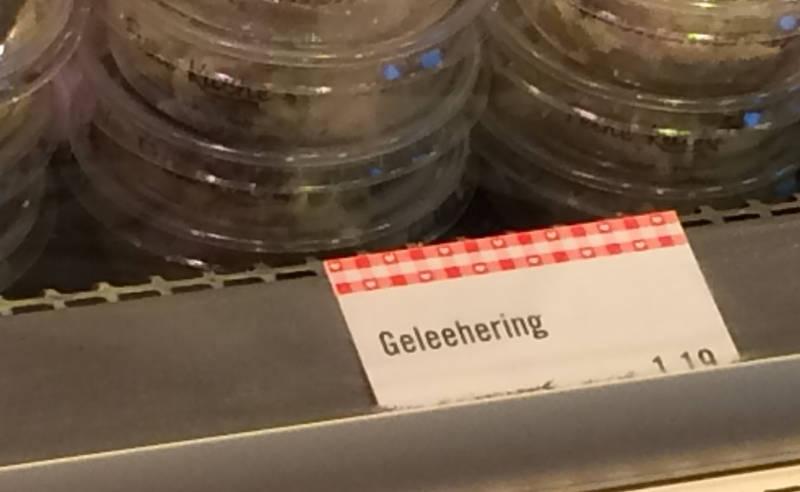
Linzer gibt’s, warum nicht auch Konzer? :-P
Eben: Konz (von lateinisch Contionacum) ist eine Stadt im Landkreis Trier-Saarburg in Rheinland-Pfalz. Sie ist Verwaltungssitz der Verbandsgemeinde Konz, der sie auch angehört. Konz ist ein staatlich anerkannter Fremdenverkehrsort. Warum soll es da nicht eine ortstypische Torte geben?
Neuer Trend für Frisch-Vermählte mit Metallallergien: der Gelee-Ehering, hier im Foto allerdings noch nach vorreformierter Rechtschreibung ohne dreifach-e.
Knifflig auszusprechen: Geschäftschance
Ich verstehe das so: :-P
• Ursprünglich schrieb man Geschäftchance oder Geschäft-Chance
• Der Rat für deutsche Rechtschreibung deutete es volksetymologisch so, daß eine Chance wie ein Sprungbrett ins Glück - also eine Sprungschanze - ist  und schlug die Schreibweise Geschäft-Schanze vor. So weit wollte der Vorsitzende Zehetmair nicht gehen. Deshalb der Kompromiß Geschäftschance
• Für 2017 hat Josef Lange angekündigt, als eine der ersten Amtshandlungen endlich die Geschäftschanze einzuführen
? Ach herrje, mir war gar nicht bewusst, wie brutal dieser üble Rat unsere Sprache vergewaltigt! Ich verspreche, sofort unser Briefpapier wegzuschmeißen und neues zu bestellen, auf dem der Chef korrekt Geschäftführer ist. :shock:
Dampflanze.
(Ich hab grad meine Kaffeemaschine repariert …)
vor 2 Stunden schrieb Kathrinvdm:
Impflücken.
Besonders knifflig, wenn man da eine Ligatur reinklatscht!
Impflücken Impflücken
Bei dieser Schrift scheint das eh „gestupst” wie gesprungen zu sein. Auf die Ligatur zu verzichten, reicht also nicht aus. Die Zeichen kommen sich zu nahe.
Mist, der Editor selbst akzeptiert das breitenlose Leerzeichen, um die Ligatur zu verhindern.
Rahaaaalf?!
Imflücken
Imf‌lücken
geht doch mit ZWNJ - und die Ligatur-Version kringelt mir meine Rechtscheibprüfung auch noch als falsch an, die mit ZWNJ nicht.
Okay. Ich dachte, das ginge auch mit U+200B.
Impflücken Impflücken
Impf‌lücken Impf‌lücken
Impflücken Impflücken
Impf‌lücken Impf‌lücken
(Ich gebe das Zeichen mit Popchar ein.)
Beim Basteln an unserer 3-Vereine-Postille stolpere ich
im einen Artikel gerade über den Dank für eine Mode-
ration eines Nachmittages ... Immer in schönen kleinen
Häppchen die modischen ... ähm ... Redebeiträge ... ;-)